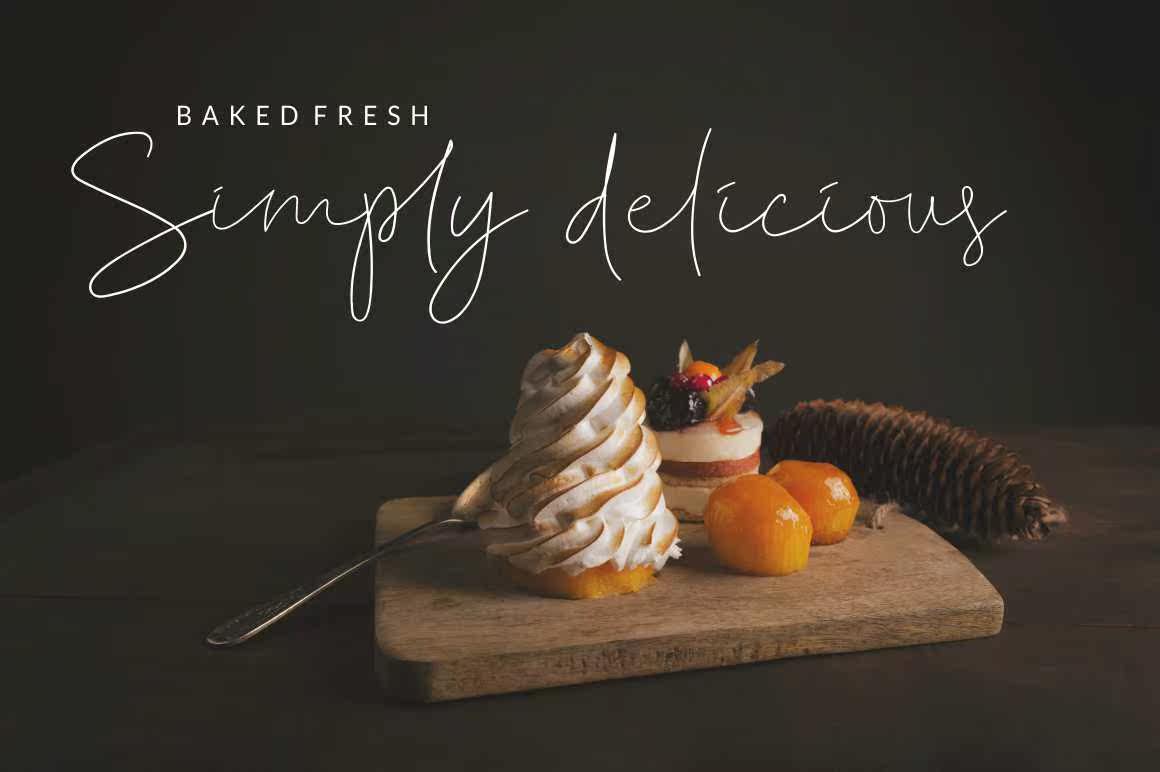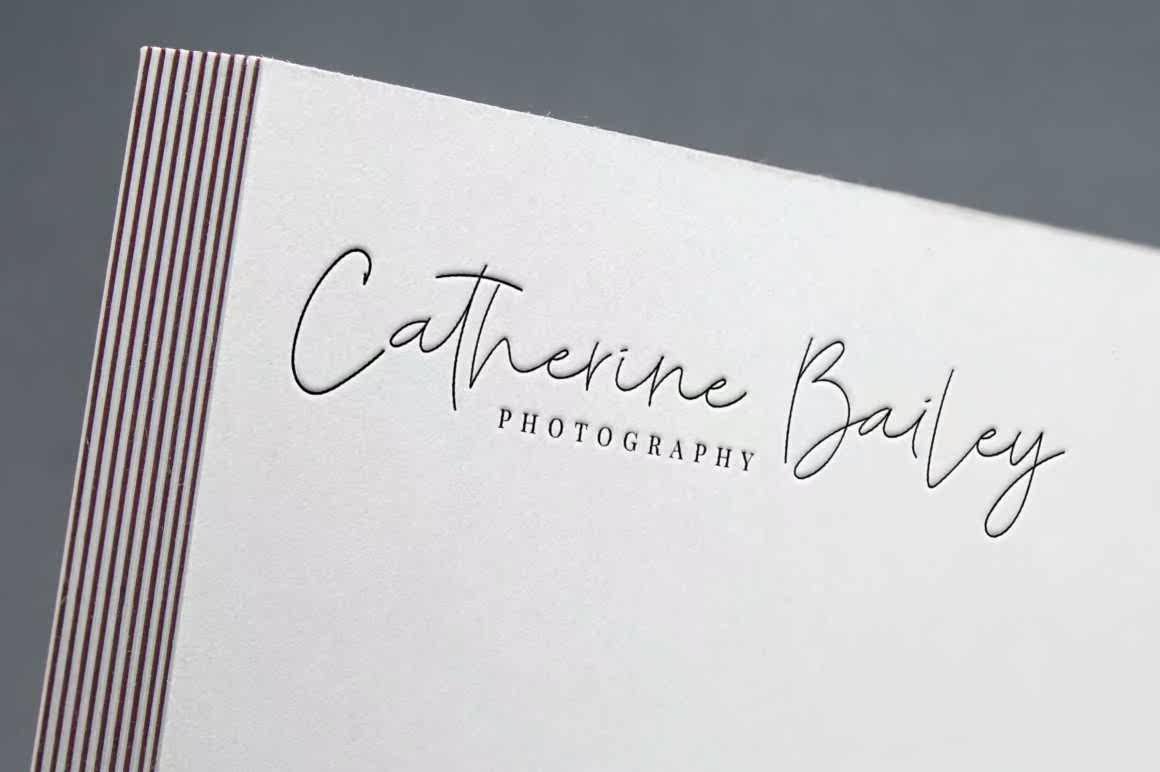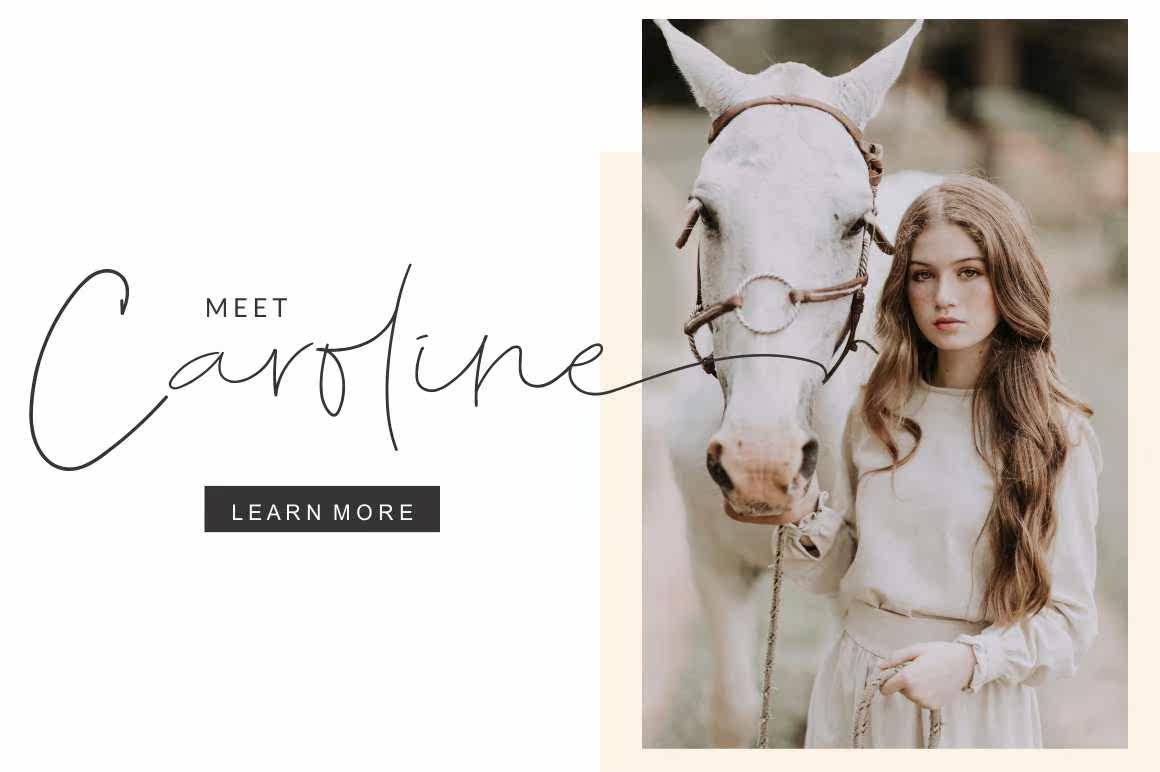
介绍–DesRosesa。Astylish Modern AlligraphyFont,带有随意手写和自然手写。它完全取代了101个自定义连字。非常适用于自选书签、品牌、t恤、婚礼、社交媒体、产品设计、文具、广告、服装、书皮、名片、贺卡、品牌、商品、,邀请函和手工报价。介绍–DesRosesa。Astylish Modern AlligraphyFont,随机手写和自然手写。它完全取代了101个自定义连字。非常适用于自选笔记本、品牌、t恤、婚礼、社交媒体、产品设计、文具、广告、服装、书皮、名片、问候卡、品牌、商品、,邀请和手工报价。